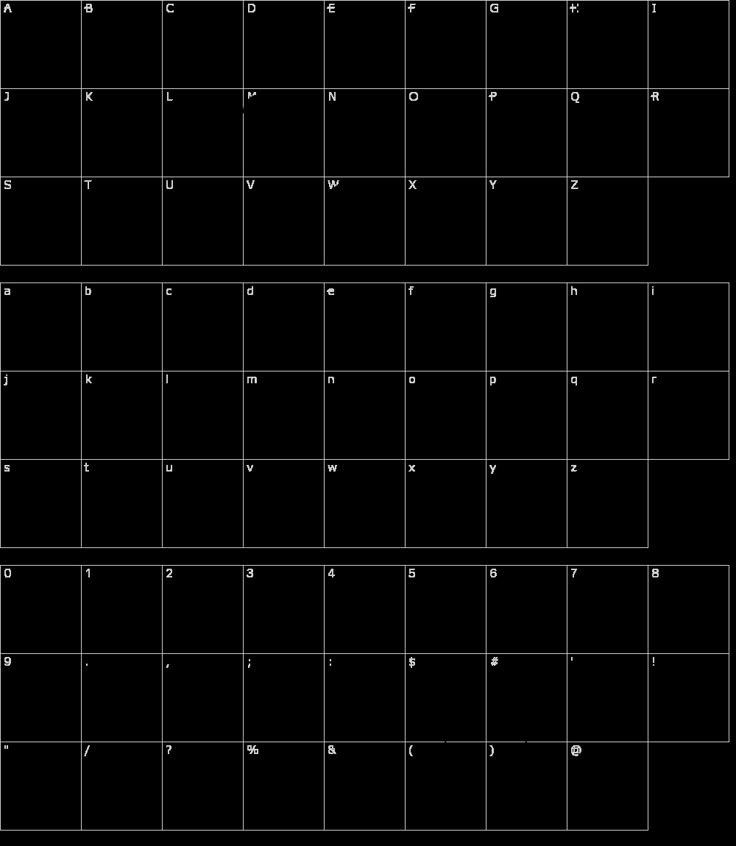
Elementary Gothic шрифт
Elementary Gothic семейство состоит из 3 шрифты
Дизайнер
Bill Roach / W. K. Roach
«Elementary Gothic» is a serif typeface that is an attempt to hybridize a decorative titling face — with a full use text face. It is a font loosely based upon medieval and renaissance era lettering, and was also inspired by the map texts of fantasy author J.R.R. Tolkien. It is a biased mixture of both contemporary and antique typographical stylizations.